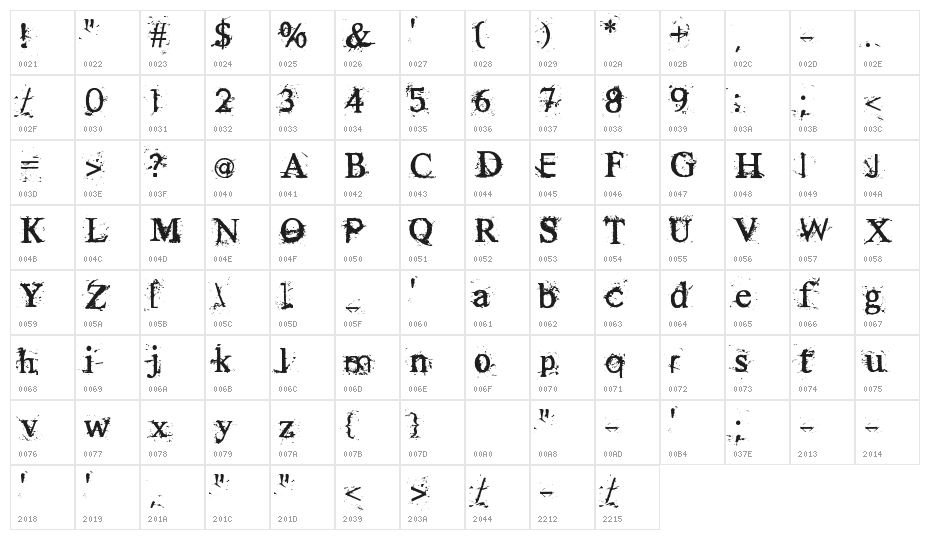
Rugged type Font
✎ Distorted Eroded
| श्रेणियाँ | Distorted Eroded |
| समग्र शैली | Vintage |
| उपयोग का मामला | Headlines, Logos |
| सुझाए गए प्रोजेक्ट | Ideal for album covers, posters, branding for outdoor or adventure-themed products, and any design needing a gritty, vintage touch. |